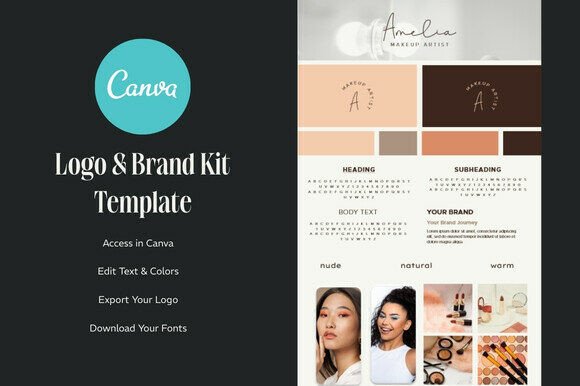
Canva Font Logo & Brand Board Template
適切なデザイン要素を見つけるのは難しい場合がありますが、Canva Font Logo & Brand Board Templateは作品を即座に引き立てる優れたコレクションを提供します。
専門家のヒント:これらの要素を補完的なフォントと組み合わせて、市場で際立つユニークで目を引くデザインを作成します。